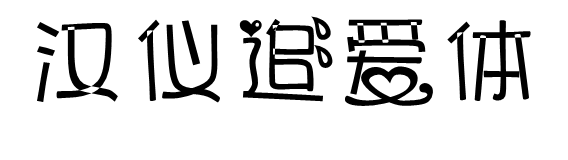
漢儀追愛體字體
漢儀追愛體是一款漢儀類賣萌可愛風格字體軟件,追愛體筆畫灑脫,整體效果顯得潦草有創(chuàng)意,加入愛心元素,比較有魅力,深受廣大年輕人喜愛,還有更多好看字體歡迎來綠色資源網(wǎng)下載體驗!
漢儀追愛體是一款商業(yè)字體,瀟灑帥氣的女性風格字體,筆畫隨意卻不失工整,非常有韻味!